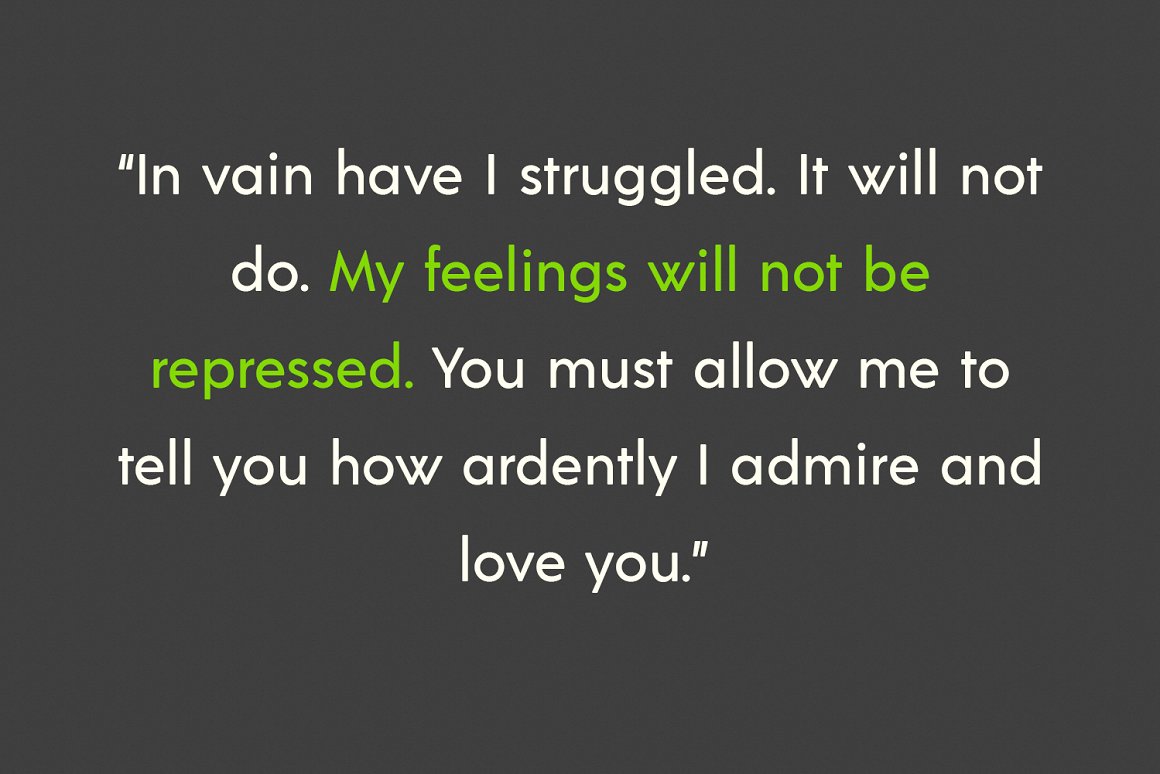
Salimo Gothic Sans Serif Font
Description de Salimo Gothic Sans Serif Font
Salimo est une police gothique moderne sans affichage. Trait régulier, caractère amusant avec un peu de ligatures et d’alternatifs. Pour vous offrir un travail créatif supplémentaire. La police Salimo prend en charge plus de 100 langues multilingues. Cette police convient à la création de logos, aux médias sociaux, aux titres de films, aux titres de livres, à un texte court, voire à une longue lettre de texte, et convient à votre police de texte secondaire avec script ou empattement. Réalisez un travail époustouflant avec la police Salimo.